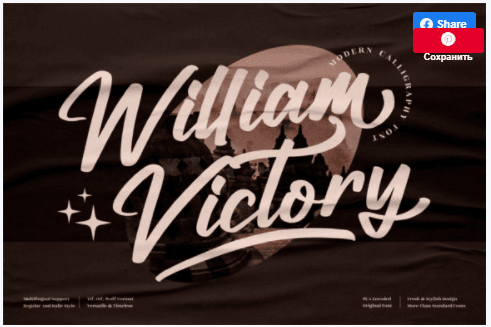
William Victory Font
William Victory - это струящийся шрифт, окрашенный кистью. Этот шрифт имеет кодировку PUA, что означает, что вы можете легко получить доступ ко всем глифам и росчеркам!
Подпадайте под его восхитительный стиль и используйте его для создания великолепных дизайнов!
William Victory - это струящийся шрифт, окрашенный кистью. Этот шрифт имеет кодировку PUA, что означает, что вы можете легко получить доступ ко всем глифам и росчеркам!
Подпадайте под его восхитительный стиль и используйте его для создания великолепных дизайнов!